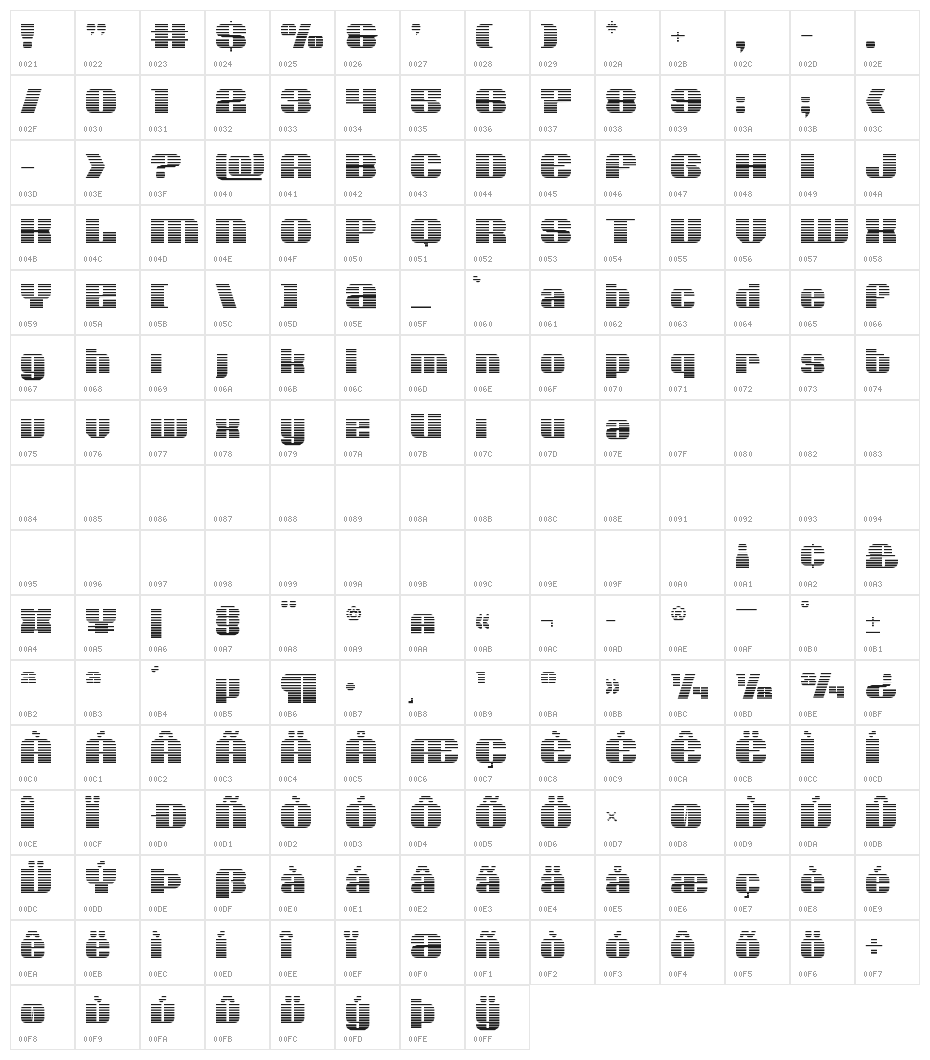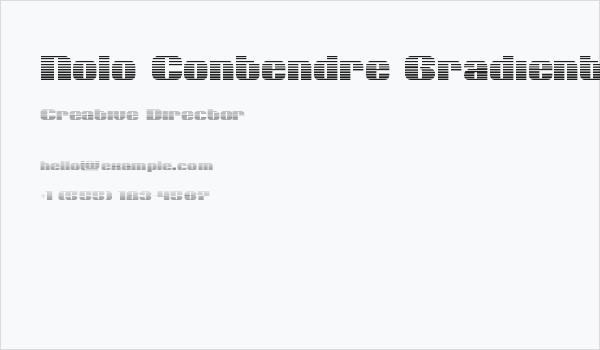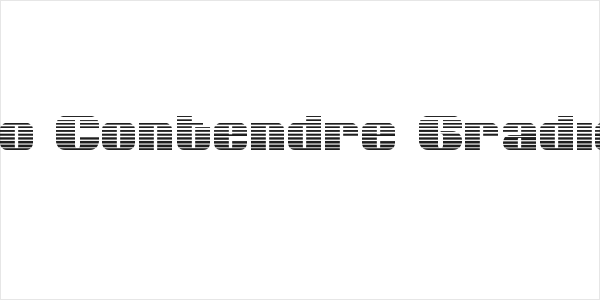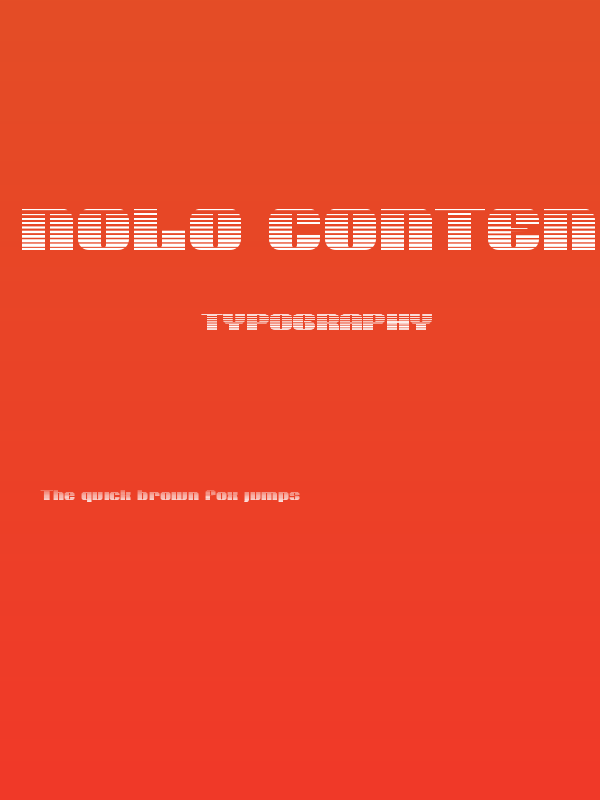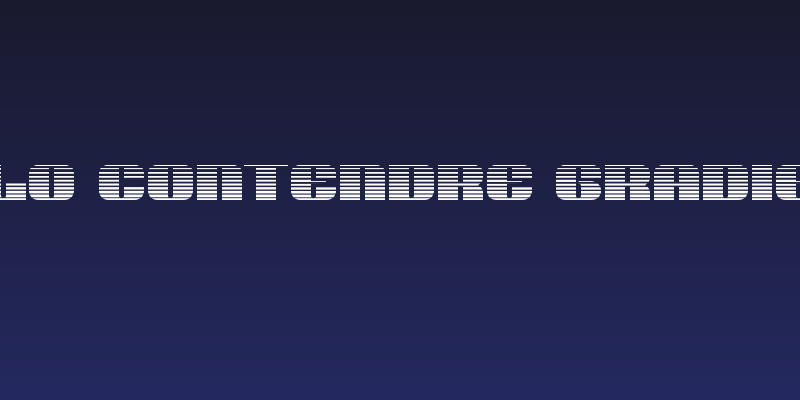
Nolo Contendre Gradient Font
| مشاريع مقترحة | Ideal for branding, posters, headlines, and any design project that requires a striking, modern aesthetic. |